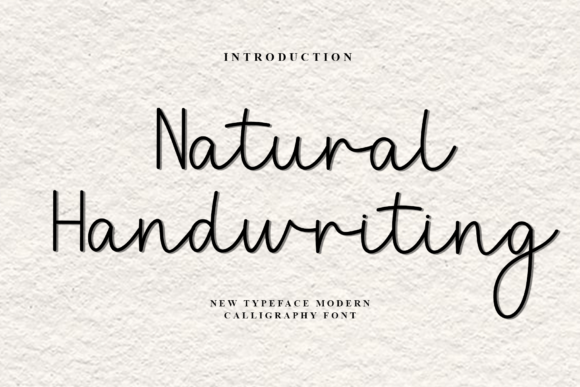
Natural Handwriting
Die richtigen Designelemente zu finden, kann eine Herausforderung sein, aber Natural Handwriting bietet eine außergewöhnliche Sammlung, die Ihre Arbeit sofort aufwertet.
Egal, ob Sie POD-Produkte (Print on Demand), Hochzeitseinladungen oder Social-Media-Grafiken erstellen, Natural Handwriting ist die ideale Wahl.